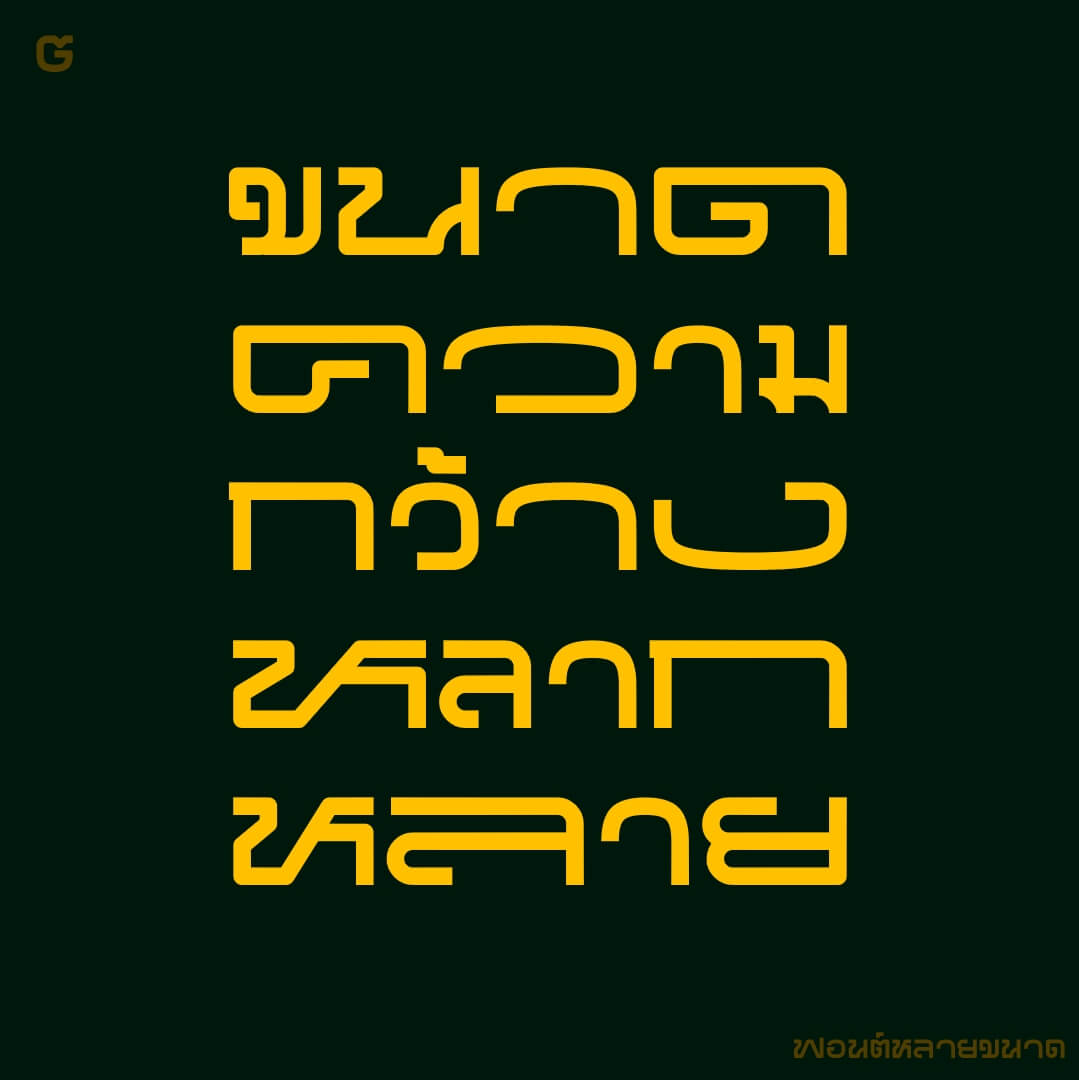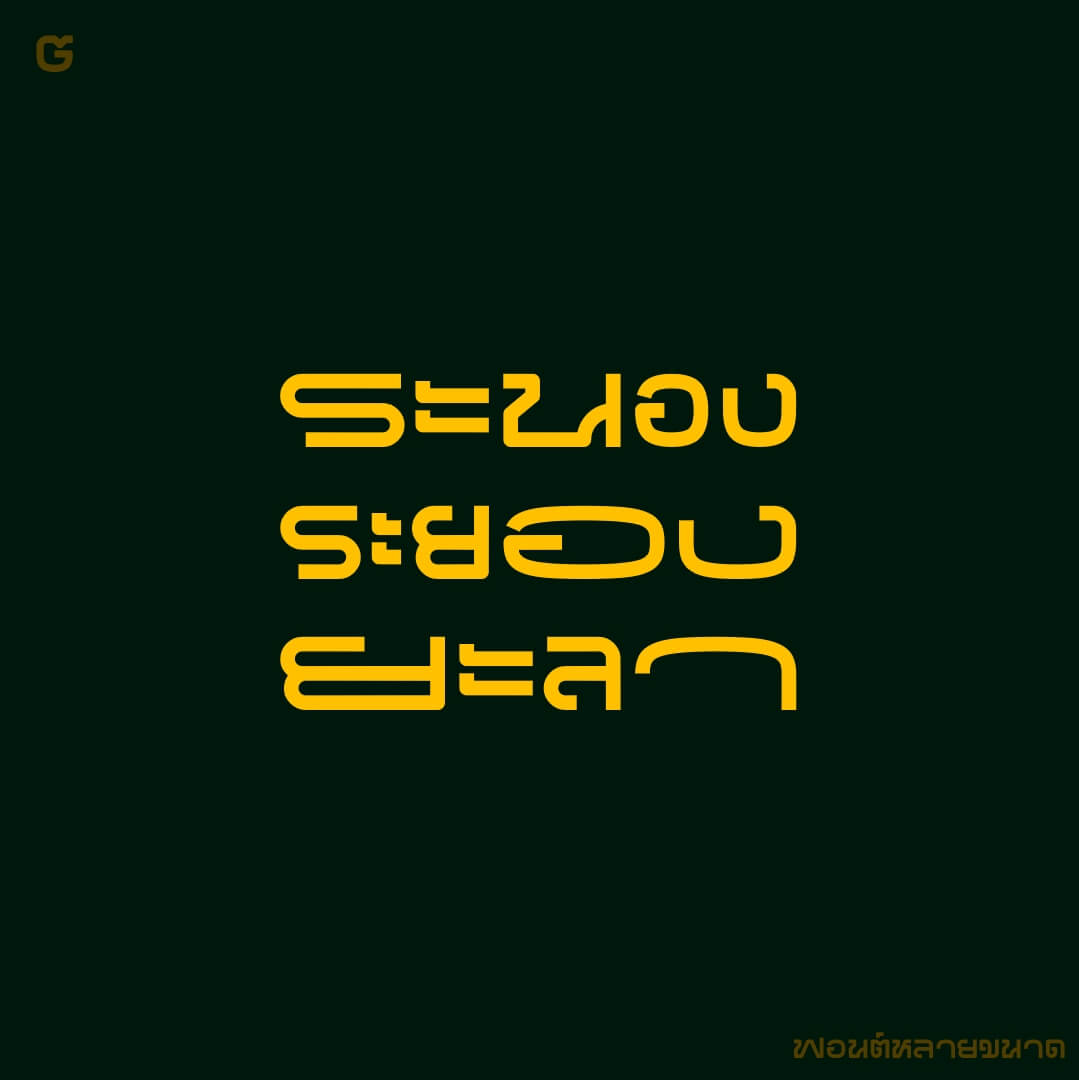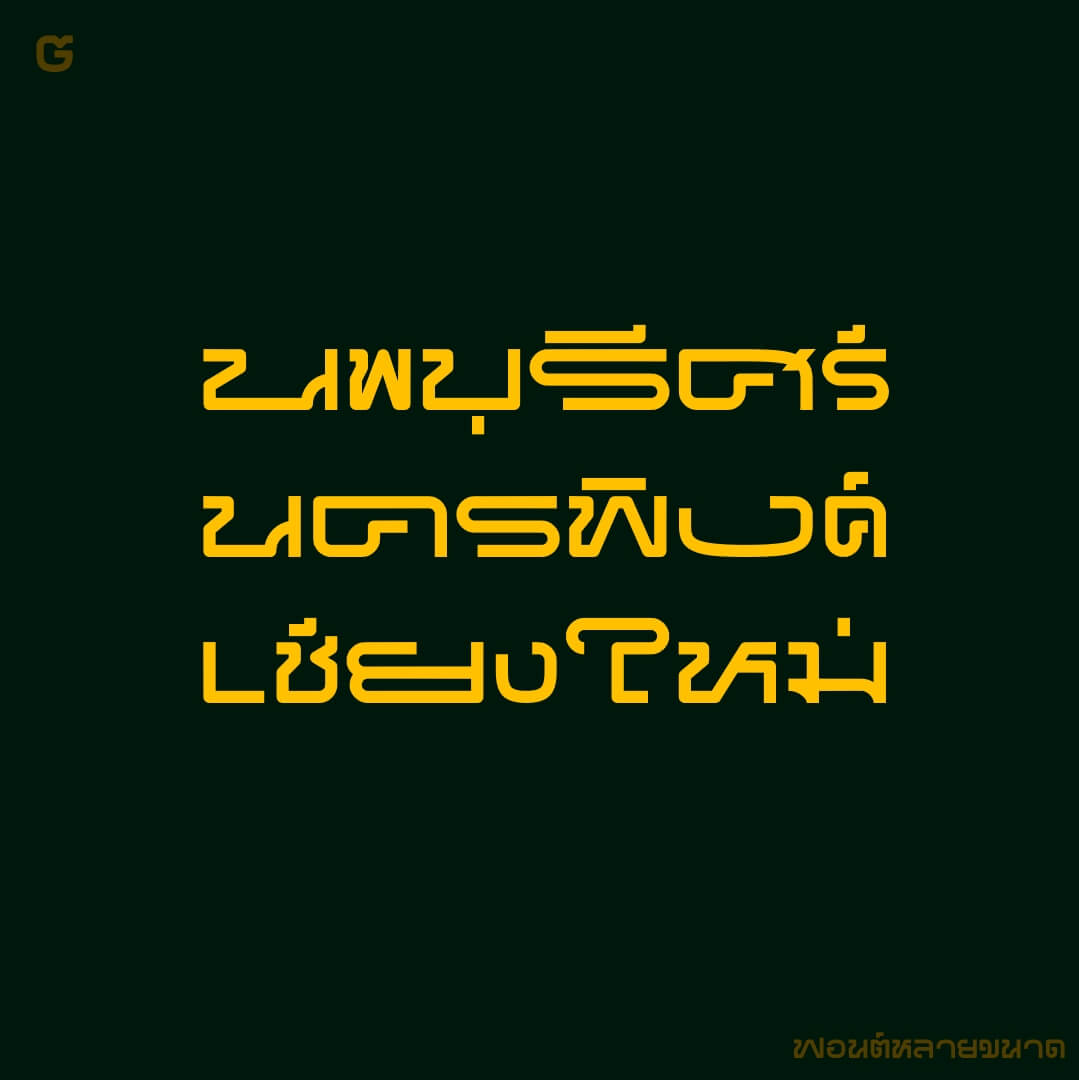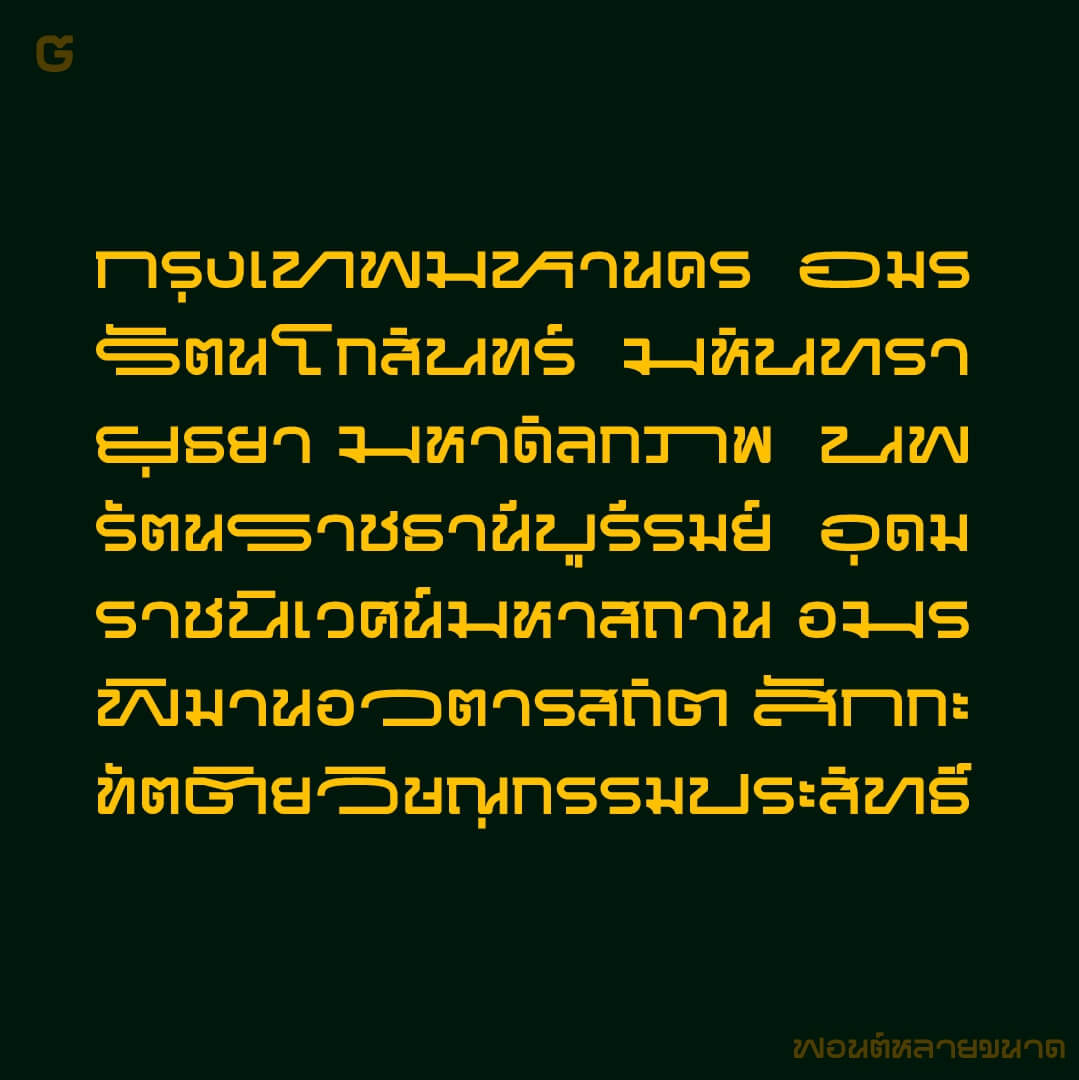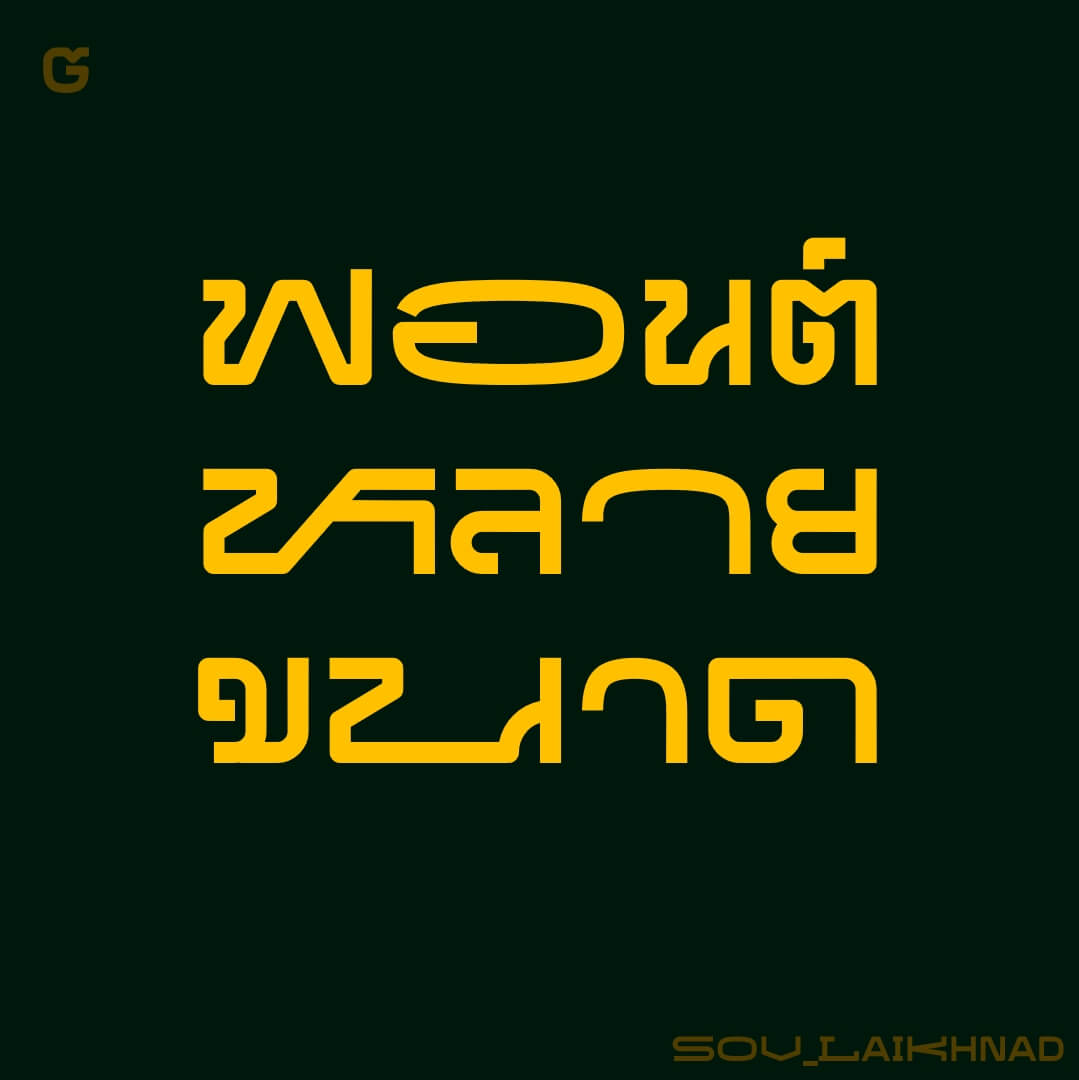
ฟอนต์หลายขนาด – ไม่ใช่ proportional space แต่เป็นอัตราส่วนความกว้าง 2 เท่า 3 เท่า ของ space
- ตัวหนาใช้เป็นพาดหัว หรือใช้กับข้อความหลายบรรทัด แต่ไม่ยาวเกินไป เอาไว้เล่นกับความกว้างตัวอักษร
เบื้องหลังการออกแบบ : ฟอนต์ หลายขนาด
หลายขนาด (SOV_LaiKhnad)